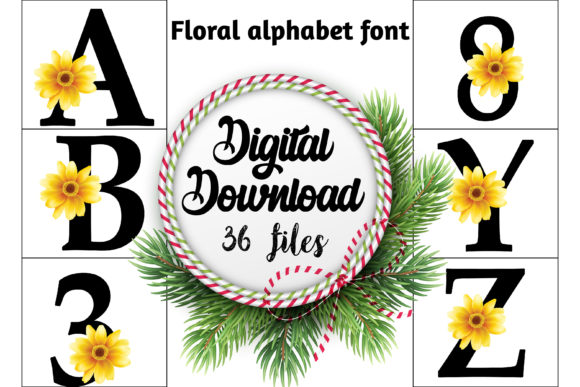
Floral Alphabet Font Set
Doğru tasarım öğelerini bulmak zor olabilir, ancak Floral Alphabet Font Set, çalışmanızı anında bir üst seviyeye taşıyan olağanüstü bir koleksiyon sunar.
İster İsteğe Bağlı Baskı (POD) ürünleri, ister düğün davetiyeleri veya sosyal medya grafikleri oluşturuyor olun, Floral Alphabet Font Set ideal bir uyumdur.